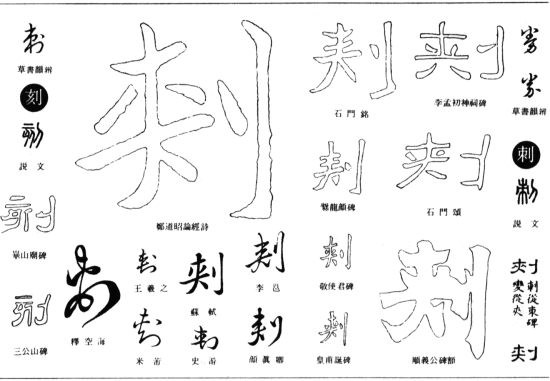
「剌す」と書いて「さす」と読む?
上のエントリの続き。
「束束」が「棘」になるんなら、じゃあ「剌」も「刺」になるんですか〜?と、当然こう思うわけです。
で、例によって五体字鑑を引いてみると、
なんと、「刺」よりも「刾」(U+523E)の方が圧倒的に多い。「剌」どころではない。
一方の五体字類には「剌」の字体が一つ見え、「剌刺元別/漢人混用」と註がある。
拓本文字データベースで「刺」を検索してみると、「刺」で登録されている画像だけでなく「刾」で登録されているものも表示される*2。これは、異体字も一緒に検索する仕様になっているため*3。
全部表示されるまでになかなか時間がかかるが、全体を見てみると数の上では 刾>剌>刺 といったところだろうか。教育部異體字字典ではこちら。「剌」は「刺」とは別字だという意識が今ではあるが、昔は必ずしもそうではなかったよう*4。
でも五体字鑑の音訓索引にあるこれは…
どう見ても誤植です。本当に(ry
追記
よく見てみたらこの画像の箇所、間違いだらけ。正しくはこう。
8 拉 302 9 剌 80 10 捋 306 14 辢 730
これはすごい。ある意味。